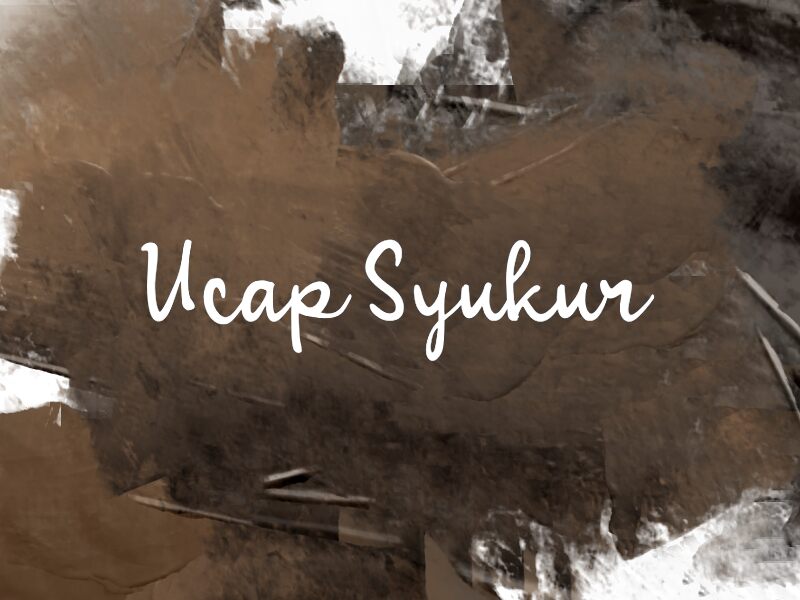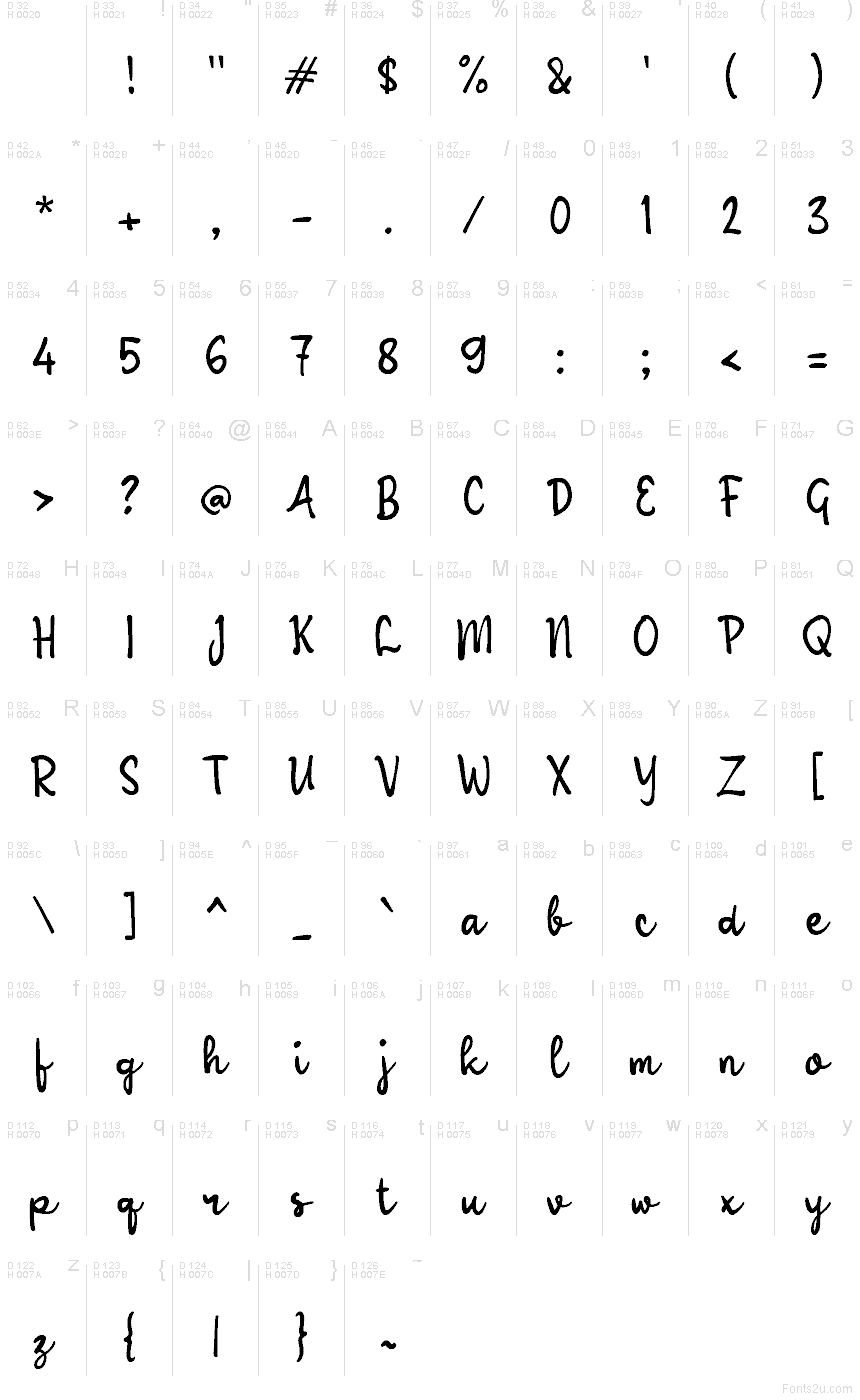
Ucap Syukur
Ucap Syukur от Wep — это бесплатный рукописный шрифт с легким, личным ритмом. Буквы выглядят так, будто они нарисованы свободной кистью: округлые штрихи, мягкие соединения и несколько вытянутых форм придают строкам непринужденное, живое движение.
Он отлично подойдет для открыток, оформления кофеен, упаковки, постов в соцсетях и цитат на картинках, где важна человечность, а не идеальная выверенность. Как бесплатный шрифт, он также хорош для заголовков, титров и простых эскизов логотипов, особенно если вы хотите, чтобы надпись выглядела так, будто она написана одним теплым жестом, а не кропотливо сконструирована.